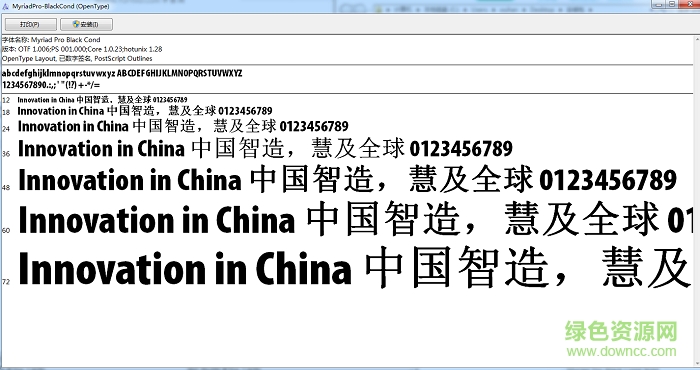
myriad pro black-黑體
myriadproblackcond字體是一款筆畫簡(jiǎn)潔干凈的英文人文主義無襯線字體,筆畫粗黑,可讀性,適用性高,極具圖形美感,需要的小伙伴快來下載吧!
人文主義無襯線字體介紹
人文主義無襯線字體是一個(gè)有機(jī)的結(jié)構(gòu),吸收了舊式的襯線字體的元素。和羅曼時(shí)代文書一樣,大寫字母有一個(gè)水平軸線,而小寫字母基于格里高利文書的模型制作。人文主義無襯線字體動(dòng)態(tài)的形狀和單色調(diào)顏色,通過不同的字母寬度調(diào)解平衡,給人溫暖友好的感覺??勺x性和友好的界面使得Myriad在印刷和顯示兩方面都表現(xiàn)出良好的適應(yīng)性。
myriad pro black